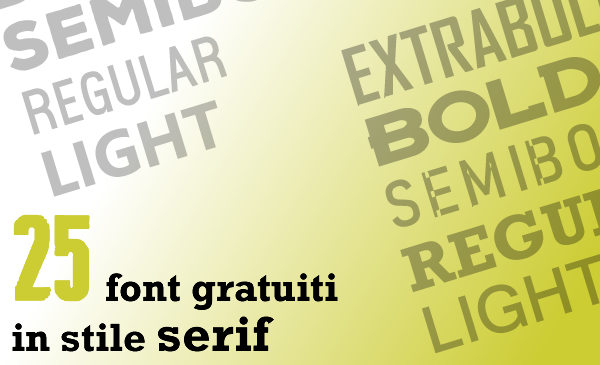
I font di tipo Serif spesso vengono utilizzati nella stampa per dare un'immagine di prestigio, raffinatezza ed eleganza.
La raccolta è composta da 25 font in stile Serif che, non solo sono gratuiti, ma soprattutto molto trendy!
25 font gratuiti in stile serif